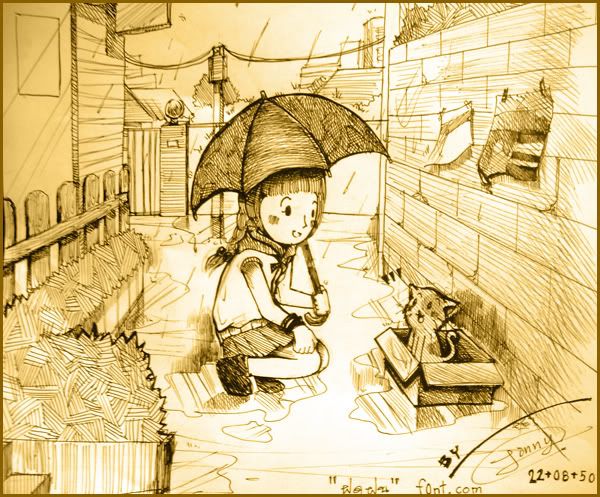
หมีน่ารัก  กรี๊ดดดดด
หมีน่ารักมากเลยยยย  กรี๊ดดดดด
น่าเอาไปทำการ์ดจริงๆ ชอบจัง
วันนี้ทำมามั่ง...แอบนั่งวาดในคาบเรียน(ตัวอย่างไม่ดี มิควรเอาเยี่ยงอย่าง)
ไม่ได้ร่าง ไม้บรรทัดก็หาไม่เจอด้วยค่ะ ฮือๆ~    ตีบเลยอาจแปลกๆนิดๆเราเพราะมั่วน่ะ แหะๆ  ฮิ้ววว
ทำเส้น สานๆๆ สนุกมากเลยรูปนี้
เอาไปใส่สีในโฟโต้ฉ่อยอีกทีนึง~ เสร็จโลด
กรี๊ดดดดด อ๊ะ น่ารักจัง เลือกสีไ้ด้น่ารักดีด้วย
กรี๊ดดดดด กรี๊ดดดดด
อย่างน่ารักเลย  กรี๊ดดดดด กรี๊ดดดดด
ยิ้มน่ารัก น้องดำ
ว้าวๆๆๆๆ  น่ารักๆๆ  ชอบตรงร่มจัง กรี๊ดดดดด
อุ้ย ชอบ กรี๊ดดดดด
น่ารักอย่างแรงเลย กรี๊ดดดดด
น่ารักอย่างแรงเลย  กรี๊ดดดดด
อุ้ย ชอบ กรี๊ดดดดด
น่ารักจัง กรี๊ดดดดด
เส้นสวย รายละเอียดดี งานน่ารัก ชอบๆ ปลื้ม